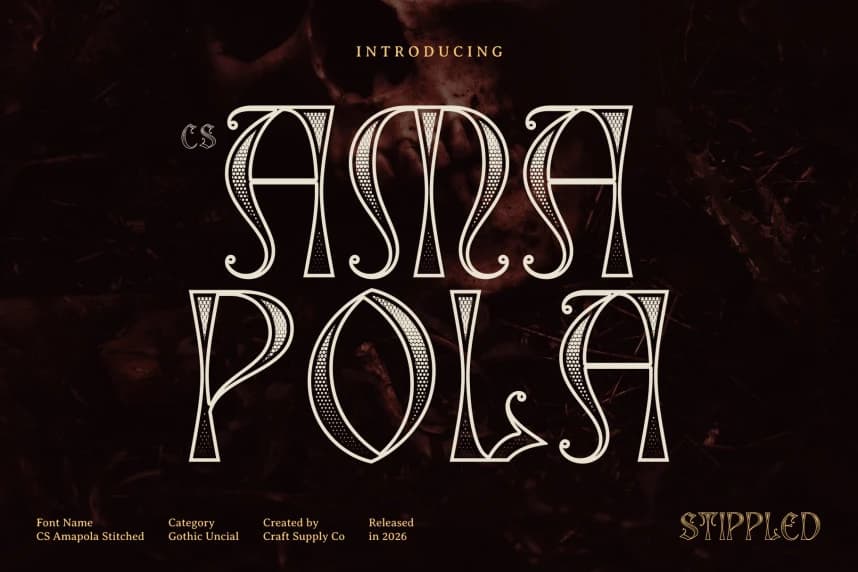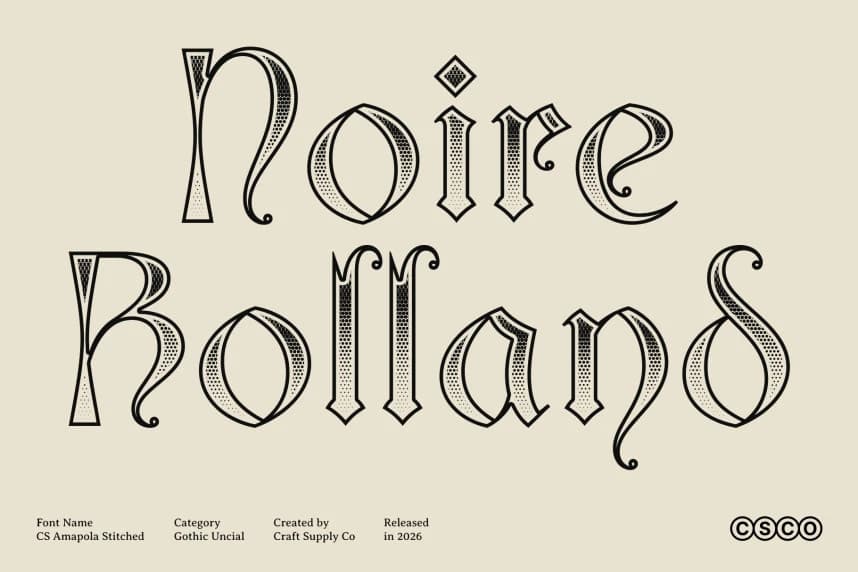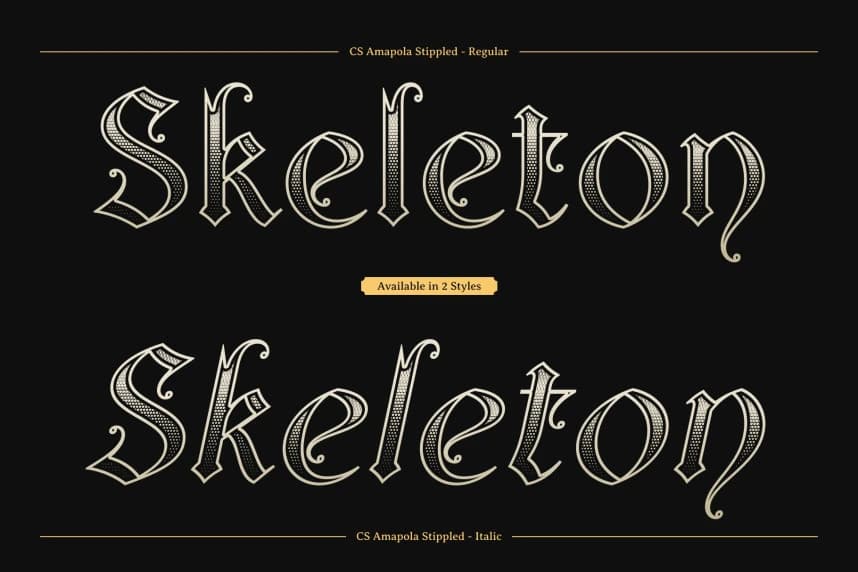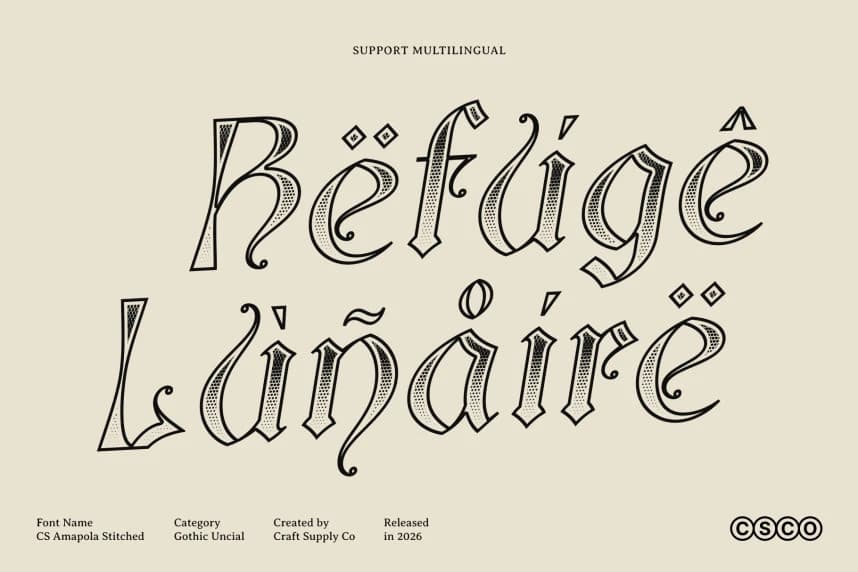
CS Amapola Stippled Font
CS Amapola Stippled Font – Gothic Uncial Display Font: Klasik Uncial Eğrileri, Gotik Güç ve Noktalı Derinlik ile. Bu, pürüzsüz olanı uyum içinde harmanlayan bir gösterim yazı tipidir.
CS Amapola Stippled Font – Gothic Uncial Display Font Classic Uncial Curves with Gothic Strength and Stippled Depth. Bu, pürüzsüzlüğü uyum içinde birleştiren bir gösterim yazı tipidir.
CS Amapola Stippled
CS Amapola Stippled Regular